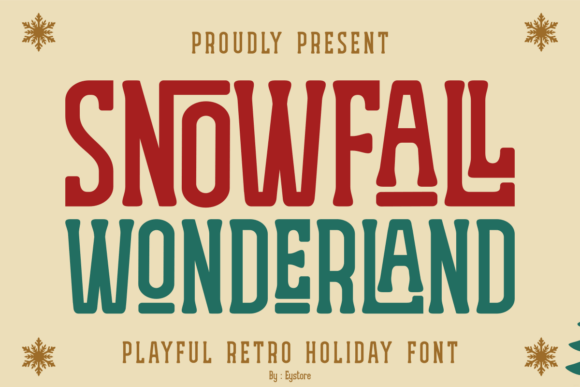
Snowfall Wonderland
Mencari elemen reka bentuk yang sesuai boleh menjadi mencabar, tetapi Snowfall Wonderland menawarkan koleksi luar biasa yang menaik taraf karya anda serta-merta.
Sama ada anda mencipta produk POD (Print on Demand), jemputan perkahwinan atau grafik media sosial, Snowfall Wonderland amat bersesuaian.